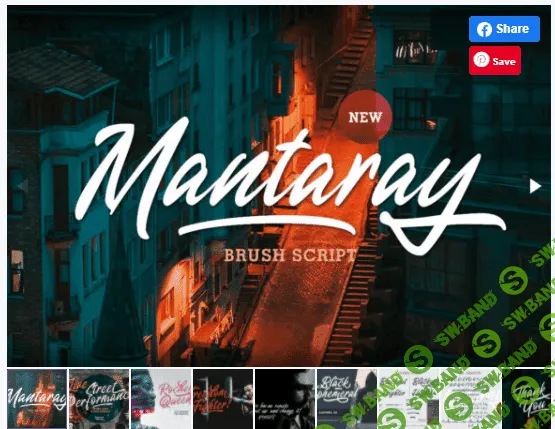
Название: Mantaray Font (2021)
[Creativefabrica] Mantaray Font (2021)
Mantaray - это изысканный рукописный шрифт, мастерски разработанный, чтобы стать настоящим фаворитом. Он сохраняет свои классические каллиграфические мотивы, но при этом выглядит современным и свежим.